Как распознать шрифт по изображению: сервисы и ограничения
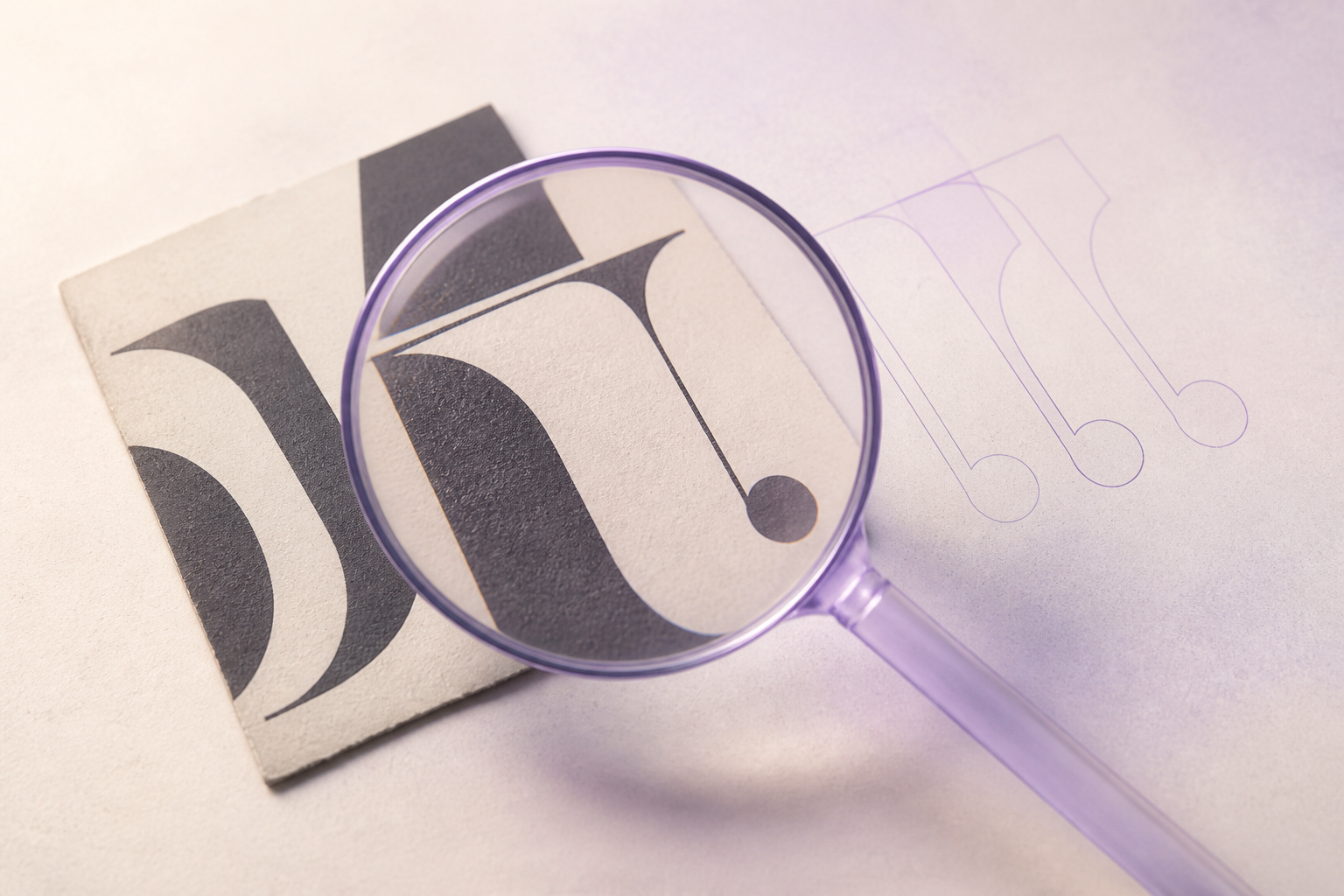
Как распознать шрифт по изображению: сервисы и ограничения
Распознать шрифт по изображению можно с помощью онлайн-сервисов, которые сравнивают форму букв с каталогами гарнитур. Лучший результат дают чёткий фрагмент текста, горизонтальная посадка и несколько разных символов. Ниже разберём подготовку изображения, популярные инструменты, ручную проверку совпадения и ситуации, когда автоматический поиск бессилен.
Что именно распознаёт сервис
Сервис распознавания шрифта не «видит» название гарнитуры непосредственно в картинке. Сначала алгоритм выделяет текст, отделяет символы от фона и анализирует очертания букв: толщину штрихов, контраст, ширину, форму засечек, окончания линий и характерные детали отдельных знаков. Затем система предлагает похожие варианты из доступной базы.
Поэтому результатом обычно становится не гарантированное определение, а список наиболее близких шрифтов. Алгоритм может найти точное семейство, если использованный текст набран распространённой гарнитурой без сильных искажений. В случае логотипа, декоративного леттеринга или изменённых букв он скорее подберёт визуальные аналоги.
Как подготовить изображение для поиска
Перед загрузкой изображения удалите всё, что мешает анализу: лишние поля, фотографии предметов, декоративные элементы и соседние строки с другим оформлением. Оставьте один фрагмент текста, где есть несколько букв разной формы. Для кириллицы особенно полезны знаки с отличительными деталями: Д, Ж, К, Л, У, ф, т и я.
- Выберите самый резкий участок изображения без размытия и сильной компрессии.
- Обрежьте фрагмент так, чтобы текст занимал большую часть кадра.
- Выровняйте строку, если она снята под углом или имеет заметную перспективу.
- Уберите фоновые детали и повысите контраст между буквами и фоном.
- Проверьте, что символы не соприкасаются и не обрезаны по краям.
- Подготовьте отдельный вариант без эффектов: тени, свечения, обводки и текстур.
- Сохраните исходник, чтобы сравнить его с результатом после обработки.
Не стоит автоматически превращать изображение в чисто чёрно-белое. Слишком жёсткая бинаризация может стереть тонкие засечки или соединить соседние элементы. Лучше начать с оригинала, затем попробовать умеренное повышение контраста и сравнить несколько вариантов загрузки.
Популярные сервисы для определения шрифта
Для первичного поиска используют несколько известных каталогов с функцией сопоставления изображения и шрифтов. Их интерфейсы, базы и условия доступа могут меняться, поэтому воспринимайте результат как рабочую гипотезу, которую нужно проверить в макете и по лицензии.
WhatTheFont
WhatTheFont подходит для быстрого поиска по фрагменту текста и часто используется как первая проверка. Загрузите изображение, выберите нужную область, если сервис обнаружил несколько строк, и изучите предложенные варианты. Полезно сравнивать не только название, но и образец букв: похожее начертание может заметно отличаться по ширине, высоте строчных знаков и характеру цифр.
Font Squirrel Matcherator
Matcherator позволяет искать шрифты по изображению в каталоге Font Squirrel. Инструмент особенно удобен, когда важна дальнейшая проверка доступности гарнитуры для проекта, однако наличие шрифта в каталоге не означает автоматически, что любая его лицензия разрешает коммерческое использование. Уточняйте условия отдельно для веба, печати, приложения или логотипа.
WhatFontIs
WhatFontIs предлагает сопоставление изображения с большой коллекцией вариантов, включая бесплатные и коммерческие решения. Такой сервис полезен, когда точного совпадения нет: по списку похожих гарнитур можно быстро перейти к визуальному отбору. При большом количестве результатов не выбирайте первый вариант автоматически — проверьте несколько характерных букв и общую плотность строки.
Пошаговый алгоритм: от картинки к рабочему шрифту
Шаг 1. Определите происхождение изображения
Сначала выясните, что перед вами: обычный наборный текст, логотип, заголовок афиши, интерфейс или отсканированная печать. Если буквы имеют разные наклоны, необычные соединения и индивидуальные пропорции, это может быть не шрифт, а ручная надпись или специально отредактированный текст. В таком случае поиск даст только близкую основу.
Шаг 2. Найдите подходящий фрагмент
Выбирайте строку, где есть не менее нескольких разных символов, а не одно короткое слово из повторяющихся букв. Например, для слова «мама» алгоритму сложнее отличить гарнитуры, чем для фразы с м, а, р, н, д и т. Не используйте фрагмент, в котором буквы закрыты графикой или сливаются с фоном.
Шаг 3. Загрузите несколько вариантов
Сделайте два-три изображения: исходное, обрезанное и обработанное с умеренным повышением контраста. Разные версии помогают понять, устойчив ли результат. Если список кандидатов полностью меняется после небольшого изменения изображения, распознавание ненадёжно и требует ручного сравнения.
Шаг 4. Сравните ключевые глифы
Откройте несколько найденных гарнитур и сравните не только общую «похожесть», но и конкретные глифы. Посмотрите на форму строчной а, двухэтажной или одноэтажной конструкции, хвост у у, верхний элемент у т, диагонали к и ж, форму цифр, точку над и и размер знаков препинания. Одно совпадение по букве не доказывает идентичность шрифта.
Шаг 5. Проверьте текст в реальном макете
Наберите исходную фразу найденными кандидатами в графическом редакторе или текстовом макете. Настройте размер, насыщенность, межбуквенное расстояние и интерлиньяж. Иногда другой шрифт выглядит убедительно после корректного трекинга, а формально точное семейство не совпадает из-за отличий в начертании, рендеринге или масштабе.
Почему распознавание шрифта ошибается
Автоматический поиск работает с изображением, а не с исходным файлом дизайна. Любая обработка меняет контуры букв: JPEG-компрессия добавляет артефакты, скриншот может сглаживать пиксели, фотография создаёт перспективу, а печать влияет на толщину линий. Чем дальше картинка от ровного цифрового образца, тем выше вероятность получить похожий, но не тот шрифт.
- Низкое разрешение скрывает тонкие засечки и детали терминалов.
- Перспектива изменяет ширину и высоту букв по строке.
- Курсив и наклон затрудняют отделение формы символа от общего поворота.
- Тени, контуры, градиенты и свечения искажают внешний силуэт.
- Сжатие букв по ширине или растяжение меняет пропорции гарнитуры.
- Необычная кириллица может отсутствовать в базе или быть заменена латинскими аналогами.
- Логотип может содержать вручную изменённые буквы, которых нет в готовом шрифте.
Как распознать шрифт вручную, если сервис не помог
Ручной анализ начинается с классификации: шрифт с засечками или без, контрастный или малоконтрастный, геометрический или гуманистический, узкий или широкий, нейтральный или декоративный. Затем выделите два-три характерных признака. Такой подход не всегда приводит к точному названию, но существенно сокращает круг поиска и помогает подобрать функциональный аналог.
Для кириллицы сравнивайте не только латинские буквы, если они есть в образце. Важны конструкция Д с нижней площадкой или без неё, форма Л, расположение перекладины у А, очертание У, характер буквы Я и форма строчной т. У одной латинской гарнитуры кириллическая версия может быть разработана иначе, поэтому совпадение английских символов ещё не гарантирует совпадение русского текста.
Практические примеры поиска
Скриншот интерфейса
Если нужно определить шрифт по скриншоту сайта или приложения, выбирайте обычный текстовый блок, а не заголовок с эффектами. Учитывайте системное сглаживание и масштаб экрана: одна и та же гарнитура может выглядеть по-разному на разных устройствах. После поиска сравните ширину кнопок, высоту строк и цифры в интерфейсе.
Логотип или упаковка
В логотипе сначала ищите повторяющиеся элементы и признаки ручной корректировки. Если одна буква заметно шире соседних, расстояния между знаками неравномерны, а окончания линий уникальны, перед вами может быть кастомное начертание. Сервис поможет найти исходный шрифт или похожую основу, но не восстановит индивидуальные изменения автоматически.
Фотография вывески или плаката
На фотографии сначала исправьте перспективу и выберите участок, где поверхность освещена равномерно. Не включайте в кадр буквы, закрытые бликами, креплениями или декоративной рамкой. Если вывеска состоит из объёмных букв, тени и отражения могут изменить форму глифов, поэтому ручное сравнение будет важнее автоматического результата.
Частые ошибки при поиске шрифта
- Загружать весь постер вместо чистого текстового фрагмента.
- Искать по одному символу или слишком короткому слову.
- Считать первый результат точным совпадением.
- Игнорировать различия между латиницей и кириллицей.
- Сравнивать только начертание, не проверяя ширину и интервалы.
- Покупать или скачивать шрифт до проверки лицензии.
- Пытаться восстановить логотип готовым шрифтом без анализа ручных правок.
Отдельная ошибка — путать шрифт и оформление текста. Иногда нужный эффект создают не гарнитурой, а увеличенным трекингом, обводкой, тенью, деформацией, капителью или нестандартным межстрочным интервалом. Поэтому при проверке воспроизводите не только сами буквы, но и параметры набора.
Чеклист перед публикацией результата
- Проверить исходное изображение и подготовить чистый фрагмент.
- Сравнить результат минимум в двух сервисах или с несколькими кандидатами.
- Проверить характерные кириллические и латинские глифы.
- Набрать исходную фразу в найденном шрифте.
- Сопоставить ширину строки, насыщенность и межбуквенные интервалы.
- Отделить точное совпадение от визуально близкого аналога.
- Проверить права на использование гарнитуры в нужном типе проекта.
Лицензия важнее одного совпадения
Определить название шрифта — только половина задачи. Перед использованием выясните, разрешена ли лицензией печать, публикация на сайте, включение в приложение, создание логотипа или передача файла клиенту. Бесплатная загрузка не равна свободному коммерческому применению, а условия могут различаться для отдельных начертаний и форматов.
Если точного совпадения найти не удалось, выбирайте аналог по задаче: для интерфейса важны читаемость и полноценная кириллица, для заголовка — характер и плотность, для фирменного знака — возможность доработать отдельные глифы. Иногда корректно подобранный аналог лучше неизвестного шрифта с неподходящей лицензией.
Можно ли точно определить шрифт по фотографии?
Иногда можно найти точное семейство, если фотография резкая, текст хорошо освещён и буквы не искажены. Однако перспектива, блики, объёмные элементы и ручные изменения снижают надёжность результата. Поэтому название из сервиса нужно подтвердить сравнением глифов и проверкой исходного макета.
Какой сервис лучше использовать для кириллицы?
Универсального сервиса с гарантированно лучшим результатом для любой кириллицы нет. Используйте несколько инструментов, загружайте качественный фрагмент и отдельно проверяйте русские буквы. Даже если сервис предлагает латинское название, убедитесь, что у выбранного семейства существует нужная кириллическая версия.
Почему сервис предлагает похожий, но не тот шрифт?
Алгоритм сравнивает визуальные признаки с каталогом, а не извлекает метаданные из изображения. Если исходная гарнитура отсутствует в базе, текст искажён или содержит нестандартные глифы, система выбирает ближайшие варианты. Чем меньше чистых символов доступно для анализа, тем шире может быть список ошибок.
Можно ли распознать шрифт по логотипу?
Можно определить шрифт-основу или найти похожую гарнитуру, но логотип часто дорабатывают вручную. Проверяйте интервалы, ширину отдельных букв, форму соединений и уникальные окончания штрихов. Если символы изменены, корректнее описывать результат как «похожий шрифт», а не как точное распознавание.
Что делать, если сервис не распознаёт текст?
Обрежьте изображение, выровняйте строку, уберите фоновые элементы и попробуйте несколько вариантов контраста. Затем загрузите более длинный фрагмент с разными буквами. Если проблема сохраняется, классифицируйте гарнитуру вручную и ищите по характерным признакам, потому что исходное изображение может содержать слишком мало информации.
Нужно ли платить за найденный шрифт?
Не обязательно: для многих задач существуют бесплатные гарнитуры, но условия их лицензий всё равно нужно прочитать. Коммерческий шрифт может требовать покупки лицензии, а бесплатная версия — иметь ограничения по проектам или распространению. Проверяйте правила конкретного правообладателя перед публикацией и передачей файлов.
Распознавание шрифта по изображению — быстрый способ сузить поиск, но не безошибочный идентификатор. Подготовьте чистый фрагмент, сравните результаты нескольких сервисов, проверьте характерные глифы, воспроизведите исходный набор и отдельно уточните лицензию. Если готовой гарнитуры недостаточно, можно создать собственный шрифт под задачу.